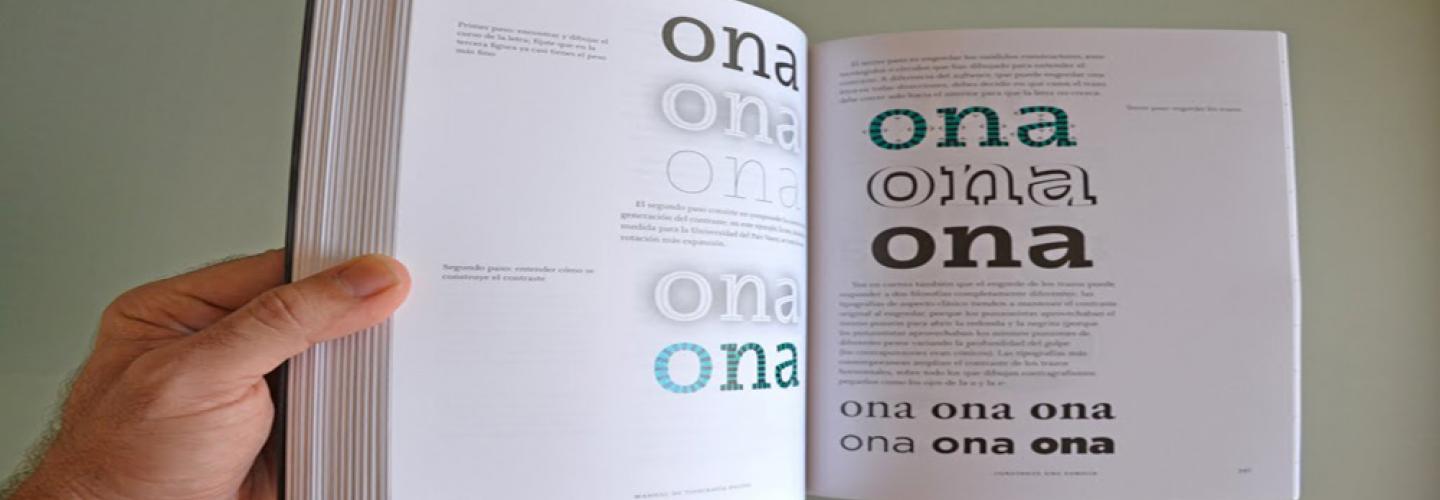
Manual de Tipografía Digital
El salto a la pantalla de la tipografía produjo una verdadera revolución. Cuando aparecieron los primeros programas para generar alfabetos, una nueva generación de tipógrafos abrió enormemente el campo de juego. Sin embargo, para la mayoría sigue siendo un misterio por qué el interletrado entre la i y la p es menor que entre la e y la n, en algunas tipografías digitales.
¿Qué es una tipografía digital?
Cuando nos referimos a tipografía digital hablamos de un grupo de dibujos de tipo vectorial, que representan letras y números y que pueden escalarse y redimensionarse sin que la calidad de dichos dibujos se reduzca. Lo consiguen gracias a los datos que incorpora cada fuente de la tipografía. A estos datos e información se les denomina hinting, que se traduce como sugerencia.
Una tipografía digital no se puede guardar en cualquier formato. Es imprescindible hacerlo en formatos específicos para el almacenamiento de este tipo de elementos. Los que más se utilizan para ello son el formato TT (TrueType), PS1 (PostScript de tipo 1) y Open Type Font. La mayoría de sistemas operativos no tienen ningún problema para trabajar con cualquiera de ellos.
¿Cuáles son las características de la tipografía?
Antes de enumerar cuáles son las características de la tipografía, es necesario conocer a qué nos estamos refiriendo. En concreto, a una técnica que se encarga de utilizar y elegir distintos tipos (es decir, letras) para la creación de tareas y trabajos de impresión.
Hay que tener en cuenta que la tipografía no es lo mismo que la fuente, dos conceptos que suelen confundirse. La fuente hace referencia a un conjunto de tipos que comparten características.
Cada tipo está compuesto por diferentes elementos, sus características, que componen una fuente. La más característica es la conocida como serifa, que también se llama remate. Este concepto se refiere a la forma de la terminación de cada letra. Se suele decir que una fuente suele tener o no serifa. Es decir, que cuenta con un pequeño remate en cada letra, o no lo tiene.
La parte más importante que tiene cada letra son las astas. Estas pueden ser oblícuas (las de la V o la A), onduladas (las de la S) o transversales (las encontramos en la A y en la H).
La altura de la x, así como la de las mayúsculas, se refieren a las alturas que tienen las letras que se consideran de caja baja, y las de caja alta, respectivamente. Relacionada con la caja está el ascendente. Es decir, la parte de las letras que sobresale de la altura que tiene la caja baja. Tanto la b como la d están entre los tipos que tienen ascendente.
Opuesta a la ascendente hay otra característica de la tipografía: la descendente. En este caso es el trozo de tipo que está por debajo de la conocida como línea base de las cajas. Tanto de la baja como de la alta. La p, la g o la j son ejemplos de tipos que tienen descendente.
¿Cuáles son los elementos de la tipografía?
Los elementos más destacados de una tipografía son cuatro: justificado o alineado, espaciado, grueso e interlineado.
El justificado o justificación es la forma en la que se colocan las líneas en la caja de las letras. Esto es, la forma en la que se alinean mediante su apoyo a un lado, al centro o centrado. La justificación puede ser en bloque, con las líneas de un lado a otro en una columna; alineadas a la izquierda, que se apoyan al lado izquierdo sin llegar al fin de la columna; alineadas a la derecha, o alineadas al centro, lo que se produce cuando se centran las de abajo en relación con las de su parte superior. Además de estas formas, las básicas, también se pueden alinear de mañera caprichosa, creando figuras alrededor de algunas que haya dispuestas.
El espaciado, que también se conoce como tracking, es el espacio que queda entre dos palabras en un texto. En cuanto al ancho, se refiere al espacio en horizontal que ocupa cada una de las letras de una palabra. Como las letras no tienen todas el mismo ancho, el espacio que separa a una de otras debe ser distinto. De otra manera, la lectura de las palabras no sería la adecuada. Esto, aunque no lo respetaron las máquinas de escribir en un primer momento, sí lo respetan los ordenadores. Por último, el interlineado es la división entre las líneas de un texto.
Manual para crear una tipografía digital
Para crear una tipografía digital, lo primero que tienes que hacer es aprender cómo está formada cada letra. Es decir, sus elementos. El siguiente paso es crear el cuerpo de cada letra, cuidando sus dimensiones en función de la caja. En su creación te ayudará partir de formas básicas como cuadrados, triángulos o círculos.
Tras darle la forma básica llega el momento de definir los elementos de cada letra. Es algo a elegir con cuidado, pero es posible que te quedes atascado en este punto. Por eso también es necesario buscar inspiración en ejemplos de tipografías, e incluso en cursos de lettering y caligrafía.
Cuando tengas tu tipografía preparada a mano, es hora de pasarla a digital, para lo que puedes emplear una aplicación como Calligraphr o Fontlab. También puedes utilizar para ello Adobe Illustrator, aunque su manejo es mucho más complejo.
- Optimización. Esta mejora la calidad de la tipografía en diferentes tamaños y formatos. La optimización puede incluir ajustes en el espaciado entre letras y líneas, la altura de las letras y la densidad de la tipografía.